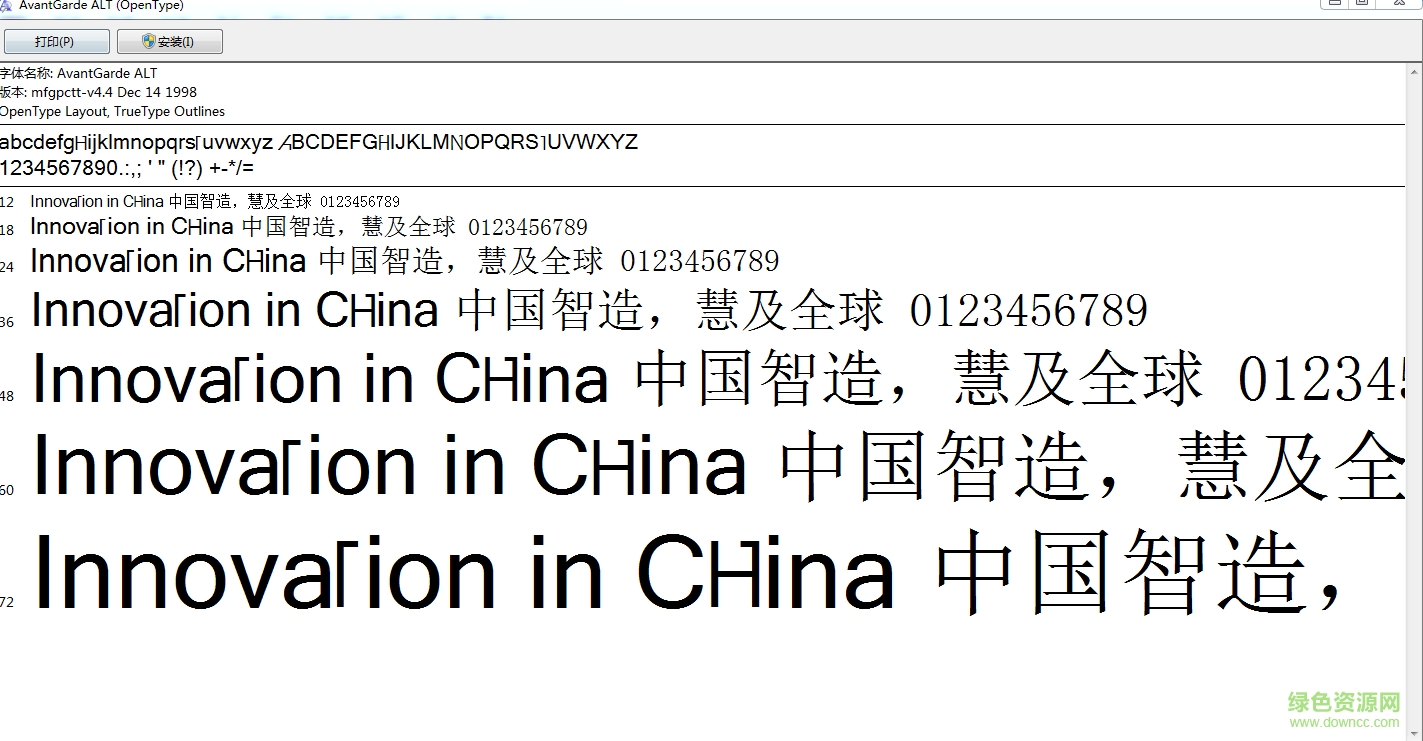
avant garde字體是一款應(yīng)用極其廣泛的英文字體,該字體線條勻稱,一筆一畫都十分規(guī)范,細(xì)節(jié)表現(xiàn)出色,需要的朋友歡迎在綠色資源網(wǎng)下載!
avantgarde字體是一款應(yīng)用于英文設(shè)計方面的字體,內(nèi)置avantgarde alt和Avant Garde Book BT兩款英文字體,該字體端正大方、結(jié)構(gòu)清晰、風(fēng)格統(tǒng)一,可用于英文書信、平面廣告、包裝印刷等應(yīng)用,喜歡的網(wǎng)友可免費下載收藏。